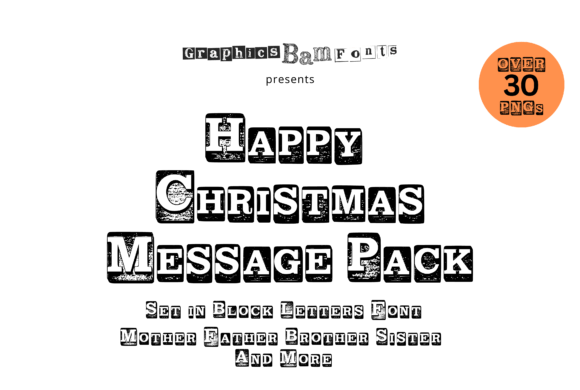
35 Happy Christmas in Block Letters Font
Пошук відповідних елементів дизайну може бути складним, але 35 Happy Christmas in Block Letters Font пропонує виняткову колекцію, яка миттєво покращить вашу роботу.